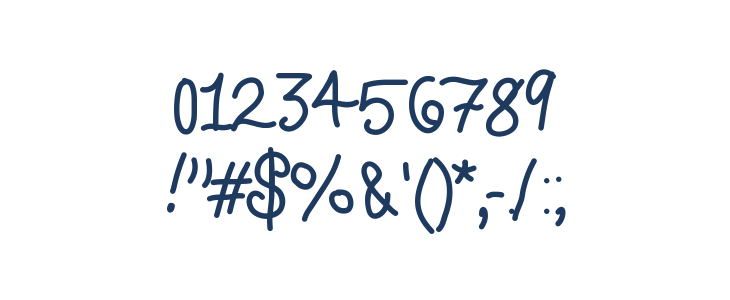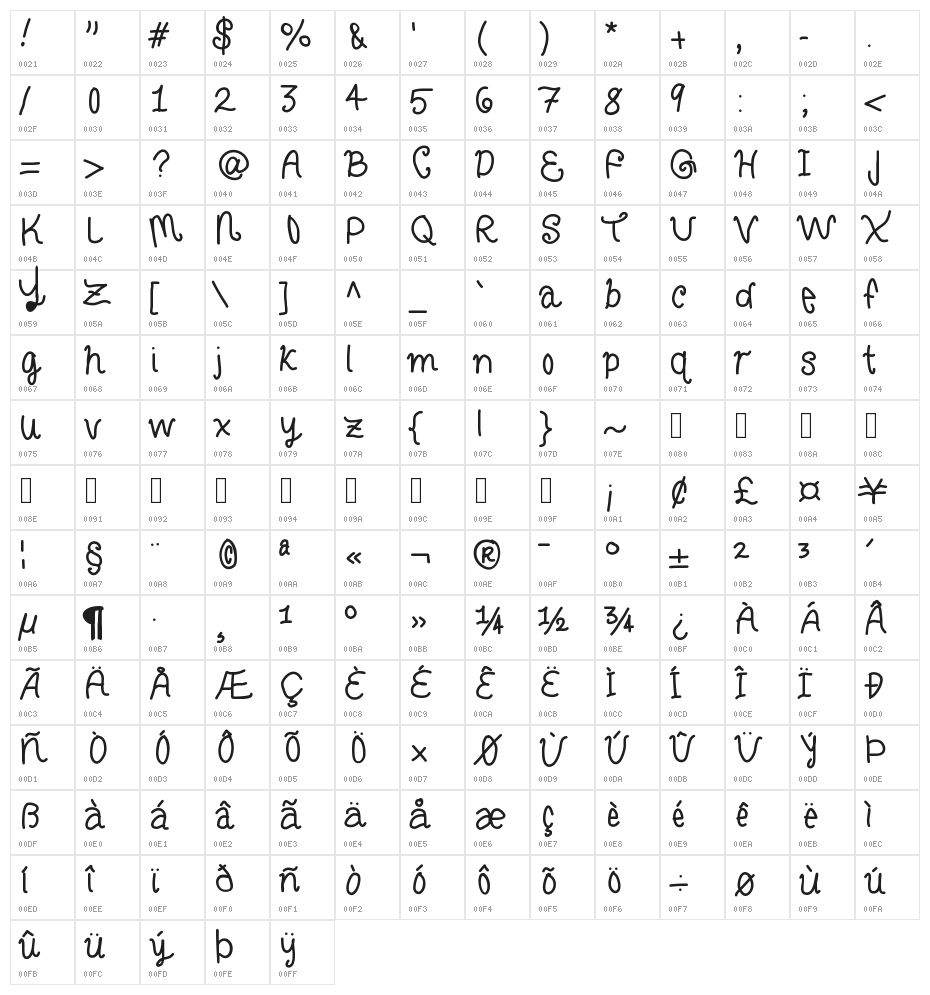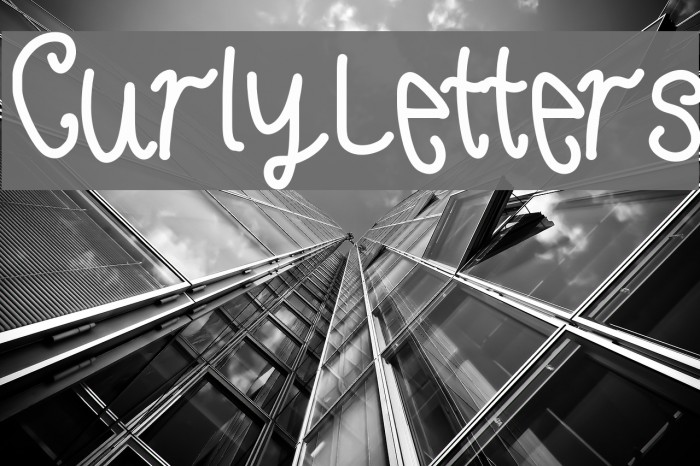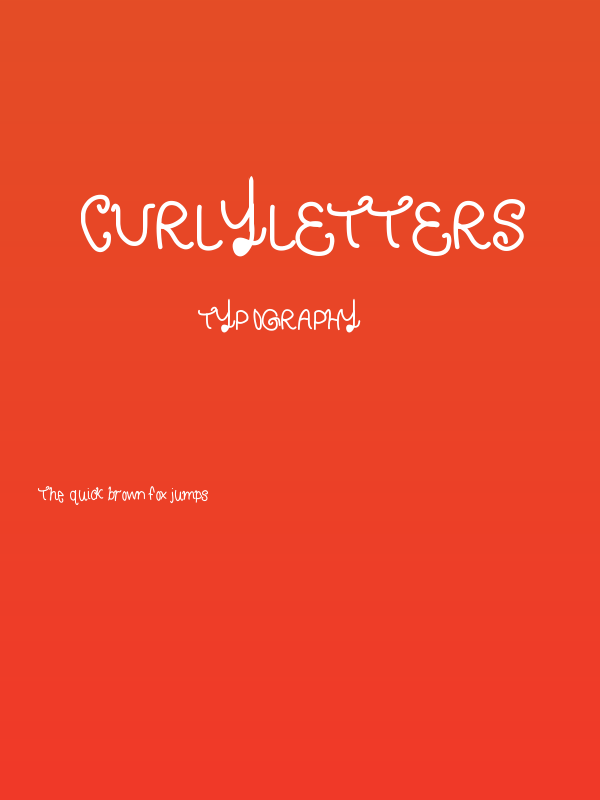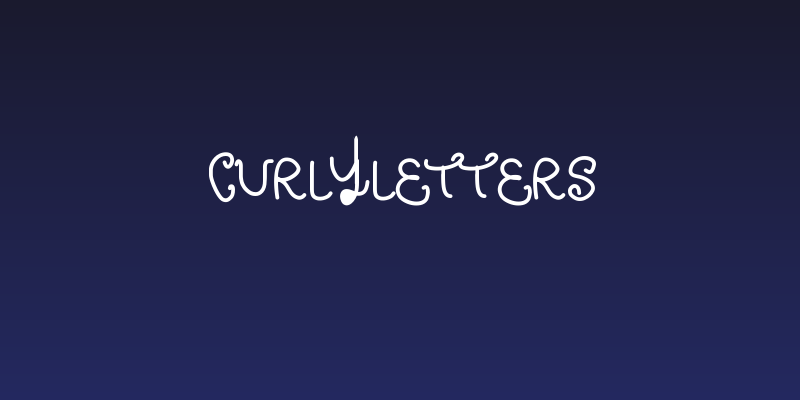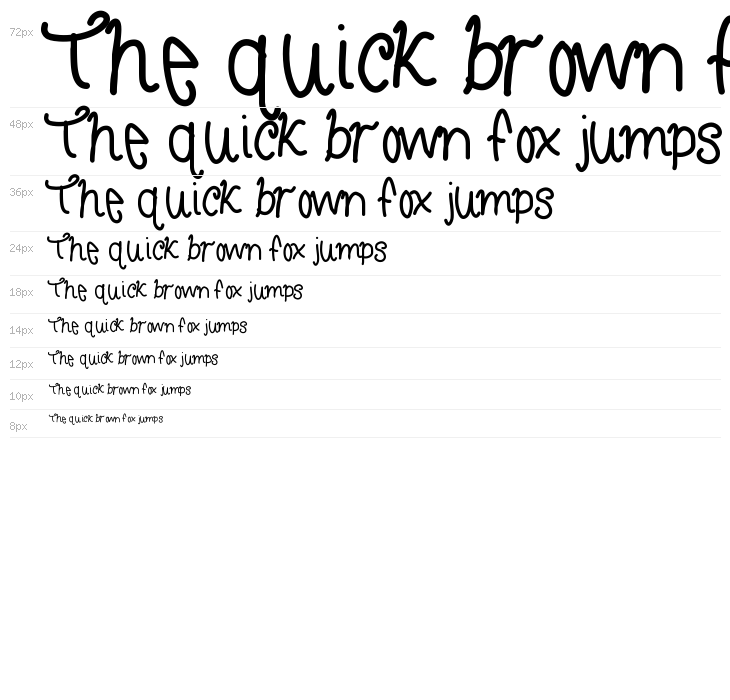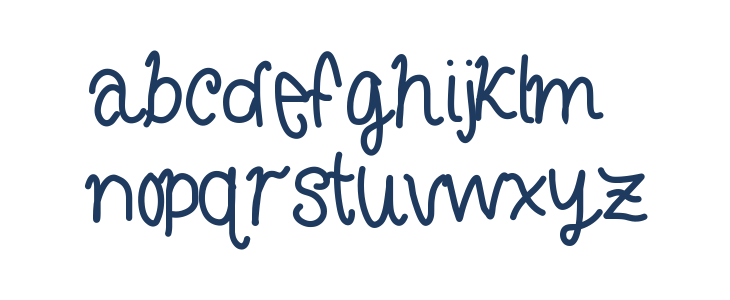
CurlyLetters Font
| Anwendungsfall | Logos, Headlines, Posters |
| Vorgeschlagene Projekte | Ideal for children's books, greeting cards, playful branding, and creative posters. |